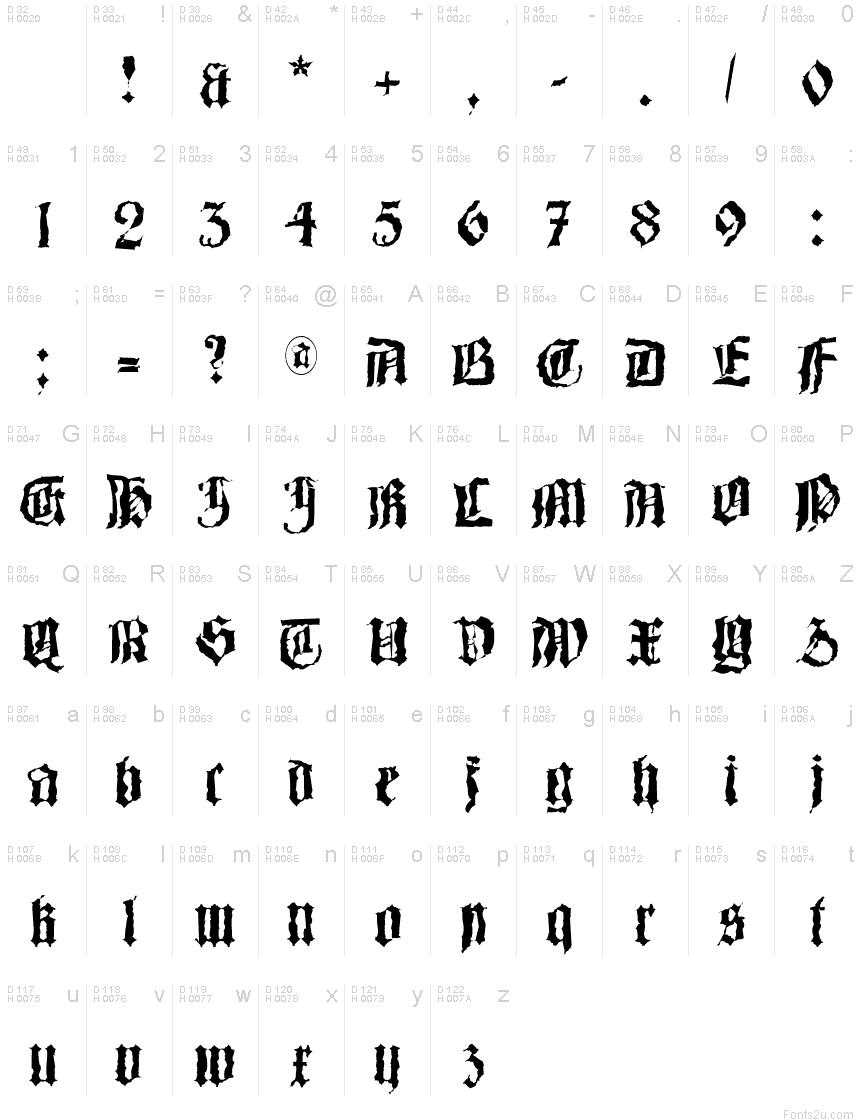
Barlos-Random autorstwa Manfreda Kleina to darmowy gotycki, średniowieczny krój pisma o surowym, „przeładowanym” tuszem charakterze, jakby wyrwany prosto ze starego manuskryptu. Jego wysokie, jeżące się znaki, połamane kąty i gęsta faktura tworzą mroczną, rytualną atmosferę, która bardziej przypomina warknięcie niż szept. Odstępy są ciasne i zwarte, dzięki czemu słowa zlewają się w surowe, czarne bloki przypominające sztandary.
Dzięki Barlos-Random nadasz metalowy klimat logotypom zespołów, okładkom książek dark fantasy, tytułom RPG, plakatom horrorów, identyfikacji wizualnej festiwali czy nagłówkom okultystycznych zinów. Ten darmowy font najlepiej sprawdza się w większych rozmiarach, gdzie jego poszarpane formy i nieregularne kontury mogą w pełni pokazać swój potencjał. Aby zachować czytelność, zestaw go z nowoczesnym, czystym krojem bezszeryfowym w tekście uzupełniającym, a Barlos-Random zarezerwuj dla najważniejszych i najbardziej wyrazistych słów na stronie.